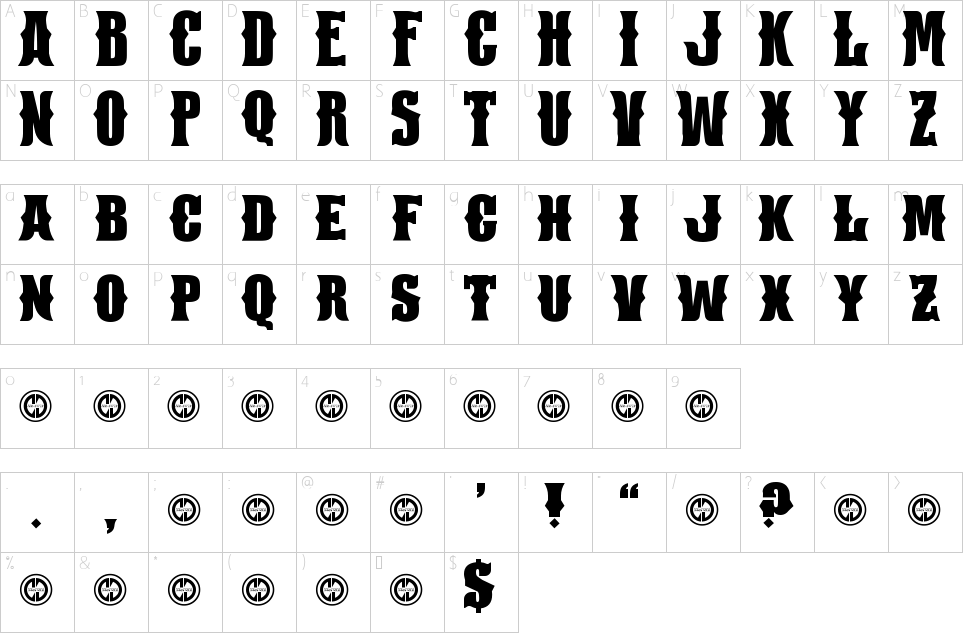
Descubra San Antonio Charros, uma fonte elegante e sofisticada que será uma ótima adição para seus projetos de design. Desenvolvida pelo Font Monger, San Antonio Charros é uma fonte charmosa e versátil, ideal para qualquer aplicação, desde criação de logotipos até design editorial. Esta fonte foi projetada para trazer ao seu design uma graça e uma modernidade inigualáveis. Com a facilidade de download disponível para Windows e Mac, é uma opção fácil e rápida para quem busca uma fonte de qualidade para seu trabalho. Até o momento, mais de 75,667 pessoas já baixaram esta fonte. Se você busca um toque único e criativo para suas criações, San Antonio Charros é uma excelente escolha. Não perca tempo, baixe-a hoje e descubra como ela pode transformar seus projetos de design.